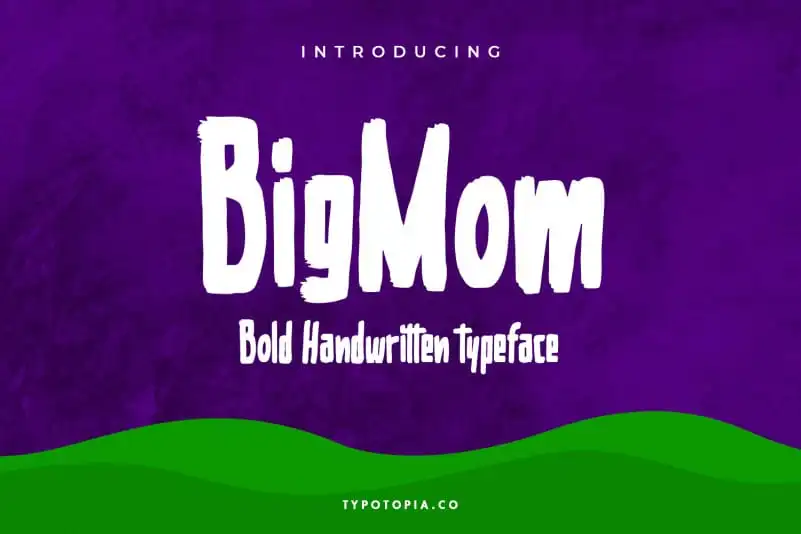
Bigmom Bold Handwritten Font – Download Grátis
Descubra a essência única da Bigmom Bold Handwritten Font neste Display Fonts criado pela typotopia. Este é mais que uma opção estilosa para seus projetos – é um trunfo visual inovador que pode transformar qualquer design em algo realmente especial. Com linhas fluidas e personalizadas, essa fonte representa a mistura perfeita entre modernidade e charme. Seja você designer gráfico ou criativo de produtos digitais, ela oferece uma maneira única de destacar sua criação e criar um impacto instantâneo. Descubra por si mesmo o poder desta fonte que é tanto uma ferramenta como uma arte.